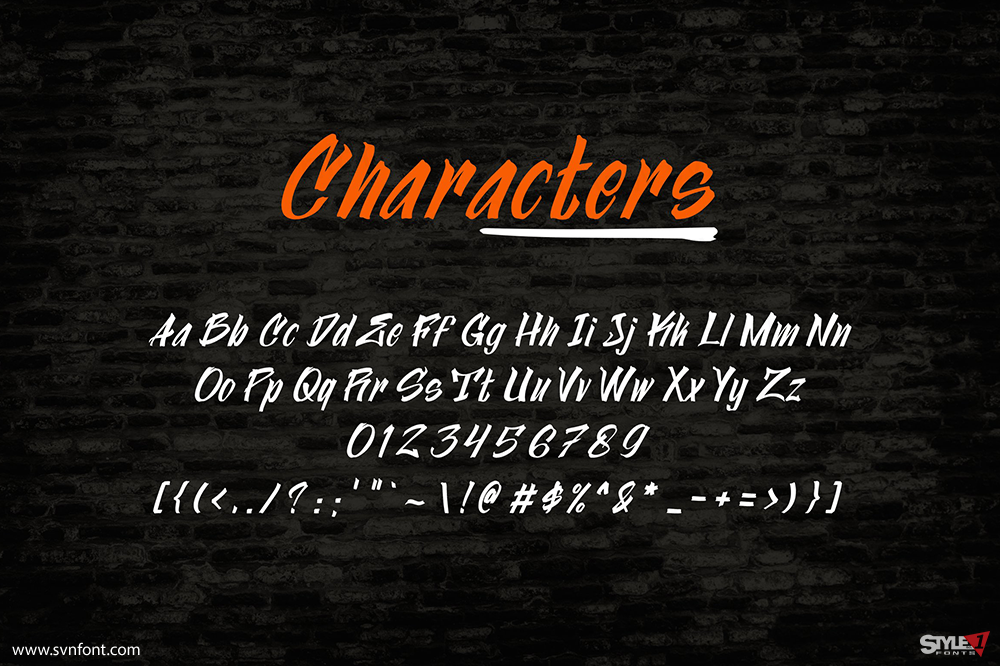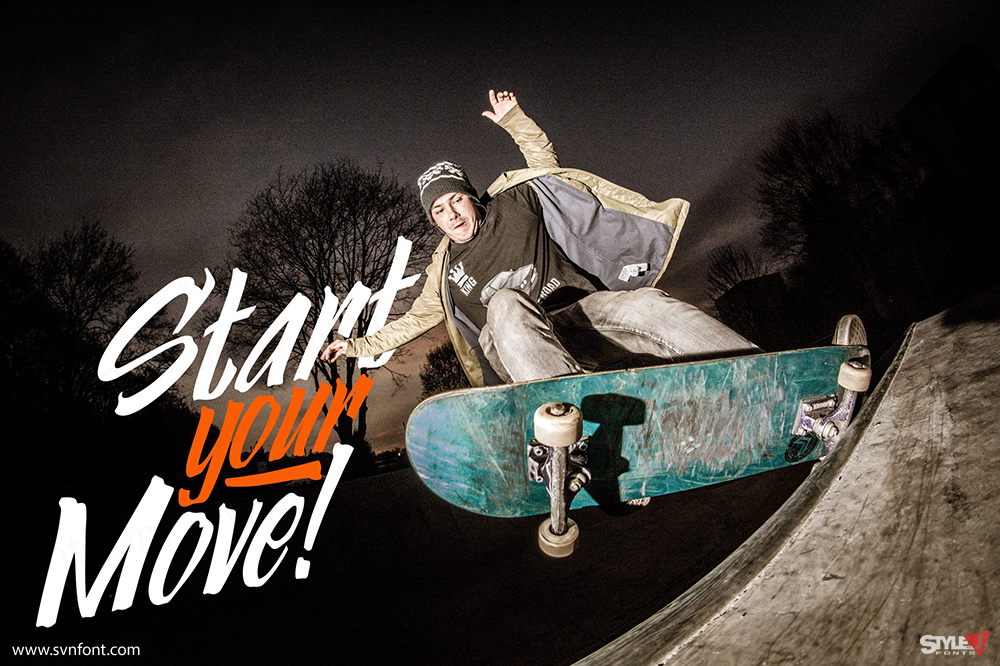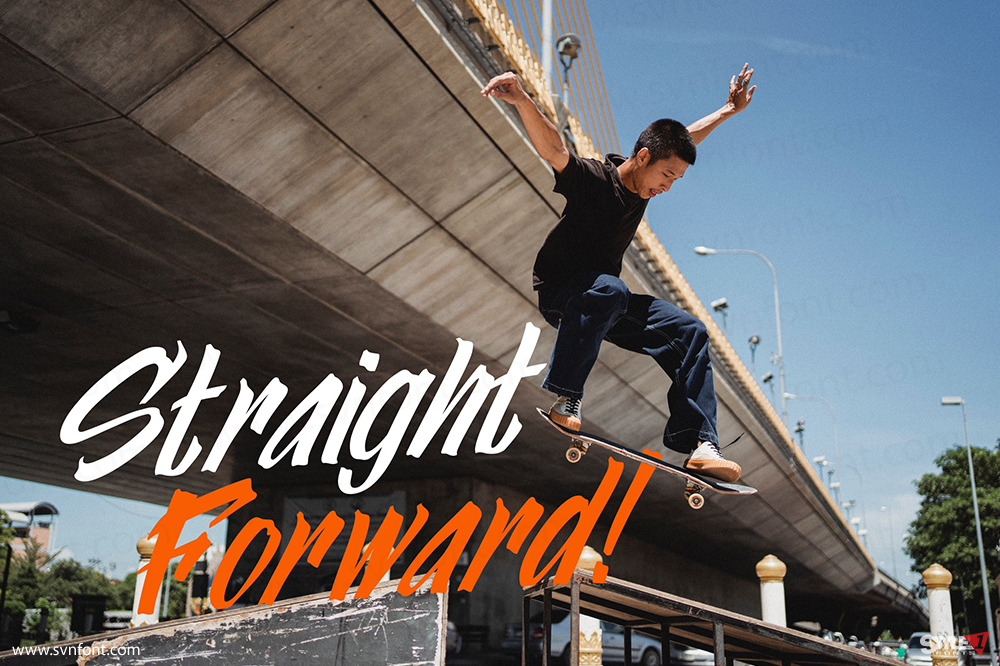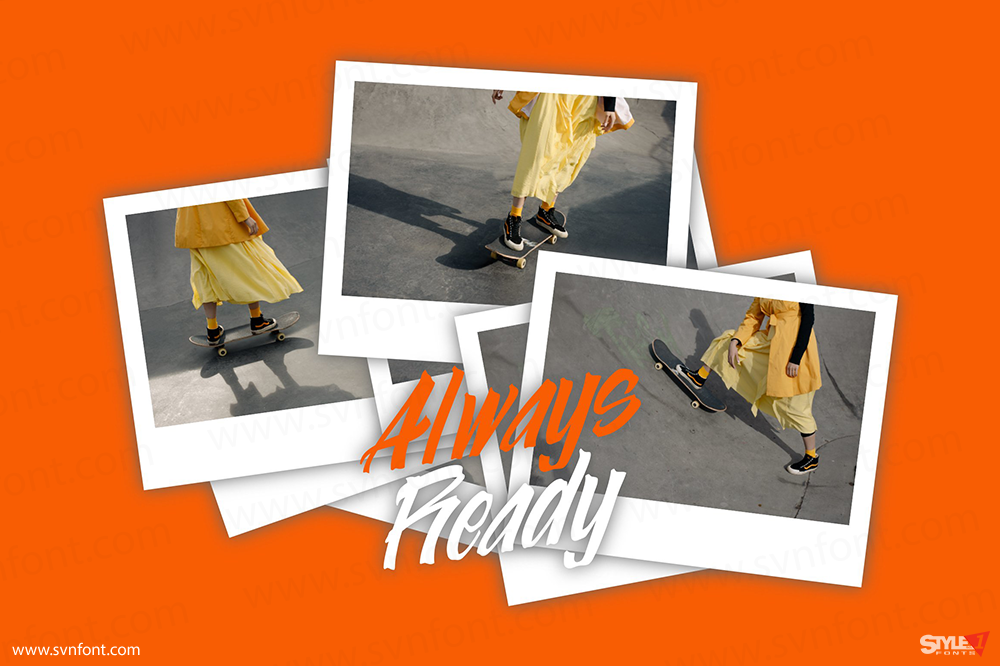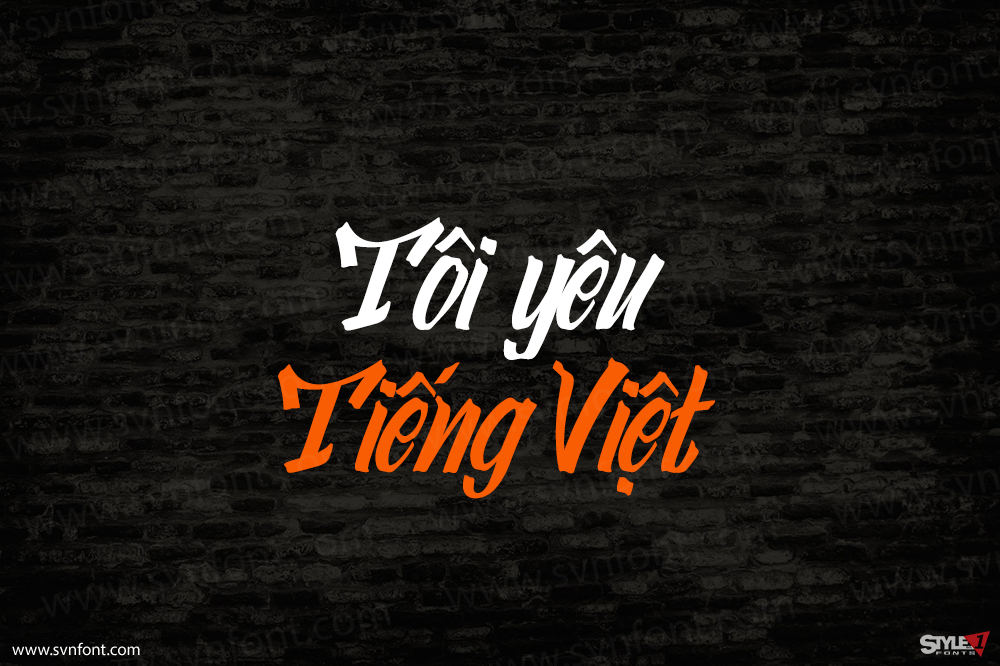
Evitrian là một font chữ hiển thị mạnh mẽ, mang phong cách đô thị. Vô cùng hiện đại và độc đáo, font chữ này sẽ làm cho mỗi thiết kế của bạn trở nên nổi bật! Rất phù hợp cho Logo, Sticker, Ghi chú, Thiệp mời, Brochure, v.v.
Nhà thiết kế: Ario Sabrang Damar
Nhà phát hành: Snape Design Studio